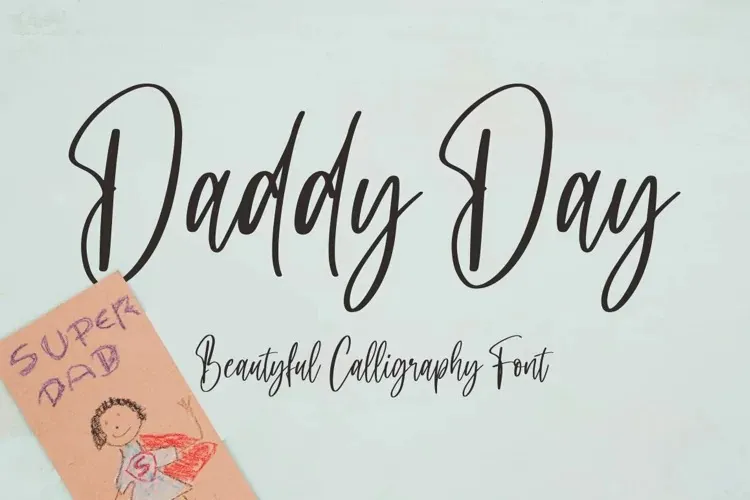
Daddy Day Font – Download Grátis
A Daddy Day Font é uma elegante fonte cursiva feita à mão, perfeita para qualquer projeto criativo. Com seu estilo natural e fluído, ela oferece uma textura autêntica que adiciona um toque de sofisticação a seus projetos. Esta fonte PUA permite acesso fácil a todos os símbolos e detalhes ornamentais, que são verdadeiras obras de arte. Sujeito à diversas aplicações, esta elegante fonte é ideal para trabalhos digitais como blogs de casamento, lojas online, mídias sociais. Além disso, ela também pode ser usada na produção de produtos, como roupas, acessórios e bolsas; em estampas, pingentes e selos; até mesmo nos logotipos ou cartões de visita; e é perfeita para criar marcações em água. Essa fonte traz uma graça natural que enriquece qualquer projeto, fazendo-a uma opção incrível para designers buscando um toque atraente e único em seus trabalhos.